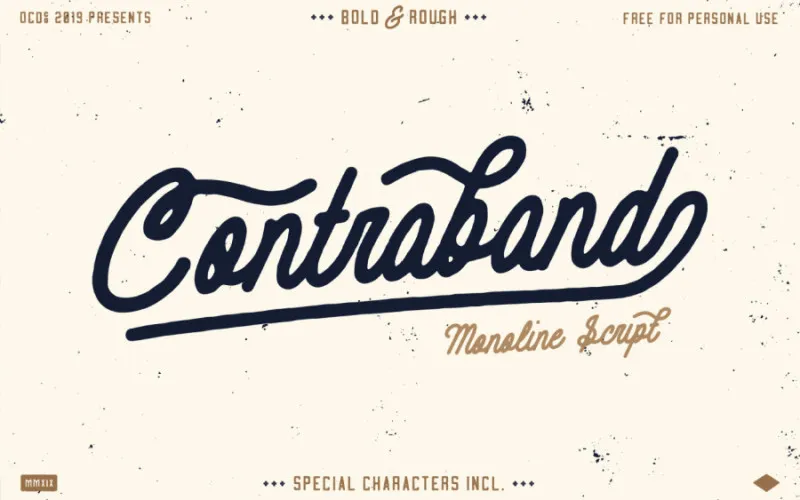
Esse é uma fonte script chamada Contraband Script Font criada pelo designer M.0Type para eventos vintage ou retro. Essa fonte tem uma personalidade interessante e vibrante, perfeita para incorporar em projetos como logotipos de empresas, produtos designados, etiquetas, postes de mídia social, roupas, convites, sinais de placas, clubes esportivos, motocicletas ou eventos especiais. Suas linhas suaves e desenhadas com muito cuidado permitem que você personalize seus projetos para agradar os mais exigentes. Contraband Script Font é uma excelente escolha para quem procura um toque especial em suas criações. Não perca essa fonte única!